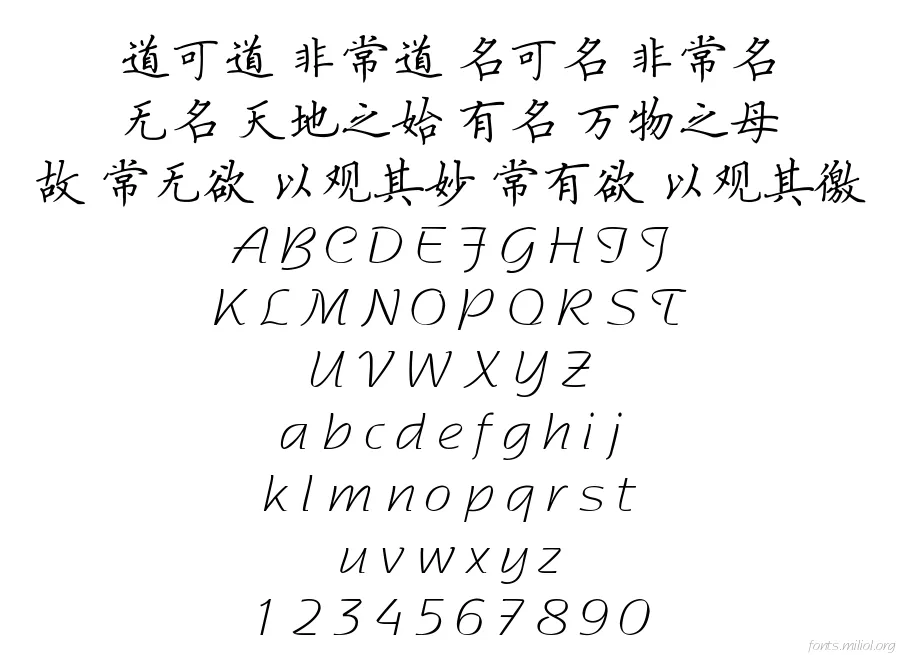
## 方正硬笔楷书简体:数字时代的传统书法之美
方正硬笔楷书简体(FZYingBiKaiShu-S15S)是一款融合传统书法艺术与现代数字技术的精品字体。这款字体以硬笔楷书为创作基础,完美呈现了中国传统书法的笔锋韵味,同时兼顾了数字环境下的清晰可读性。其标准化的字形结构和均匀的笔画分布,使文字在电子屏幕上展现出独特的艺术魅力。
作为GB1-0编码的标准字体,方正硬笔楷书简体特别适合需要展现文化底蕴的正式场合使用。无论是文档排版、广告设计,还是教学课件,这款字体都能为内容增添一份典雅庄重的气质。其笔画干净利落,转折处棱角分明,既保留了硬笔书法的刚劲有力,又符合现代审美对简洁大方的追求。
在数字化阅读日益普及的今天,方正硬笔楷书简体架起了传统文化与现代科技之间的桥梁,让用户在电子设备上也能感受到中国传统书法的独特韵味。这款字体的出现,不仅丰富了中文数字字体的多样性,更为传承和发展中国书法艺术提供了新的可能性。